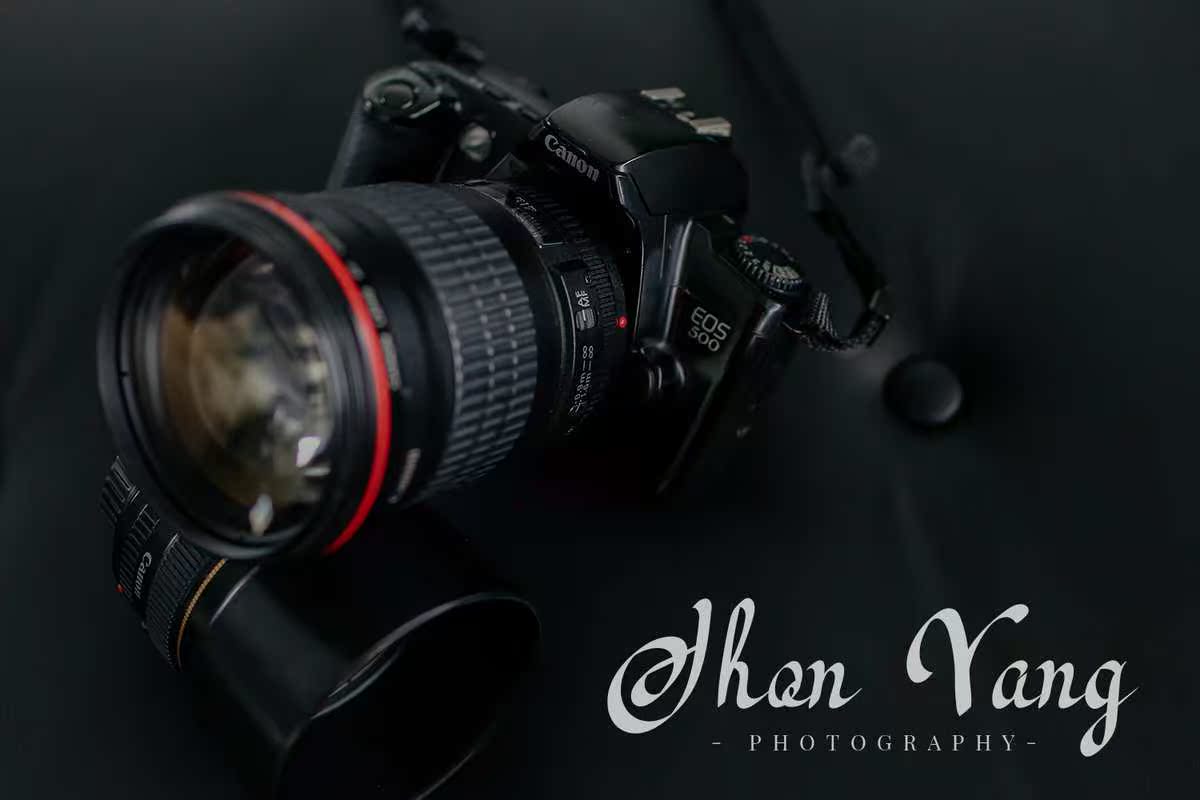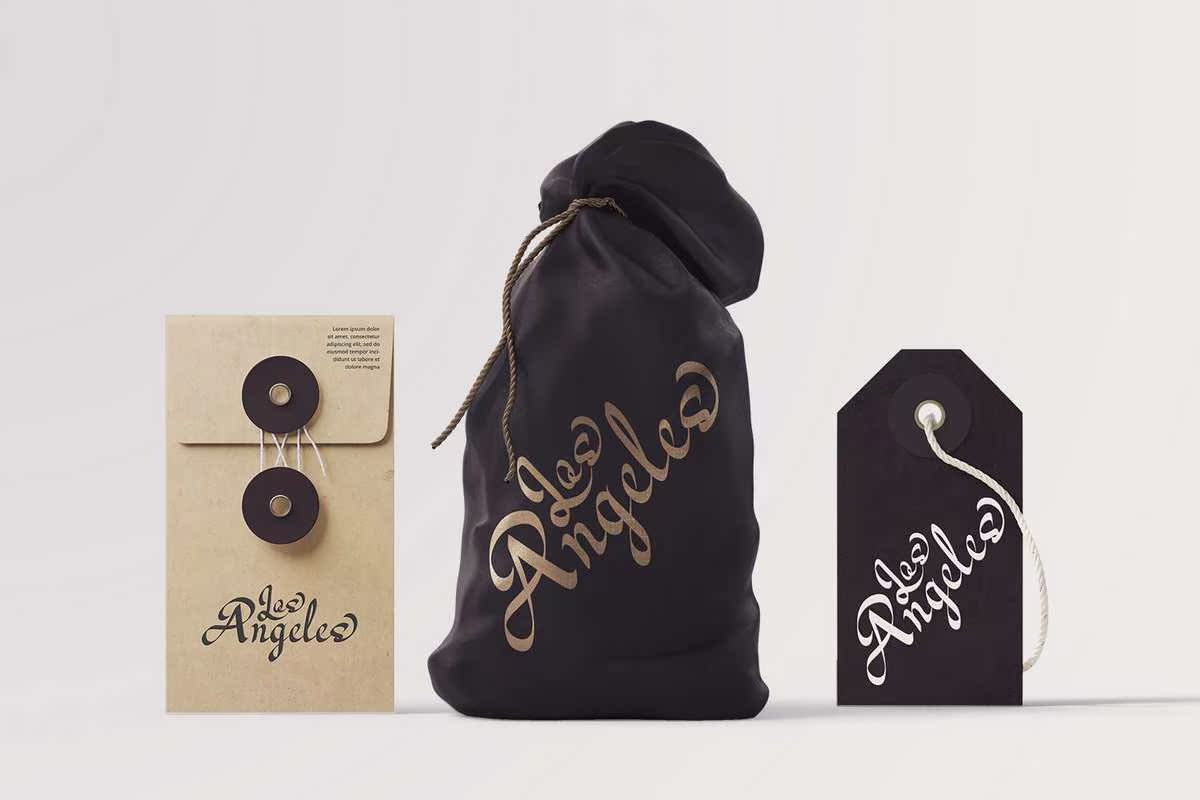
LosangelessisStylishHandRittenFont适用于任何项目,包括徽标、品牌项目、家居设计、产品包装、杯子、报价、海报、购物袋、t恤、书皮、名片、邀请牌、欢迎卡、标签、照片、水印、特价、,以及所有其他需要手写品味的可爱项目。Losangelesis Stylish手写字体将适用于任何项目,包括徽标、品牌项目、家居设计、产品包装、杯子、报价、海报、购物袋、t恤、书皮、名片、邀请卡、欢迎卡、标签、照片、水印、特殊物品、,而你所有的其他可爱的项目都需要手写的味道。